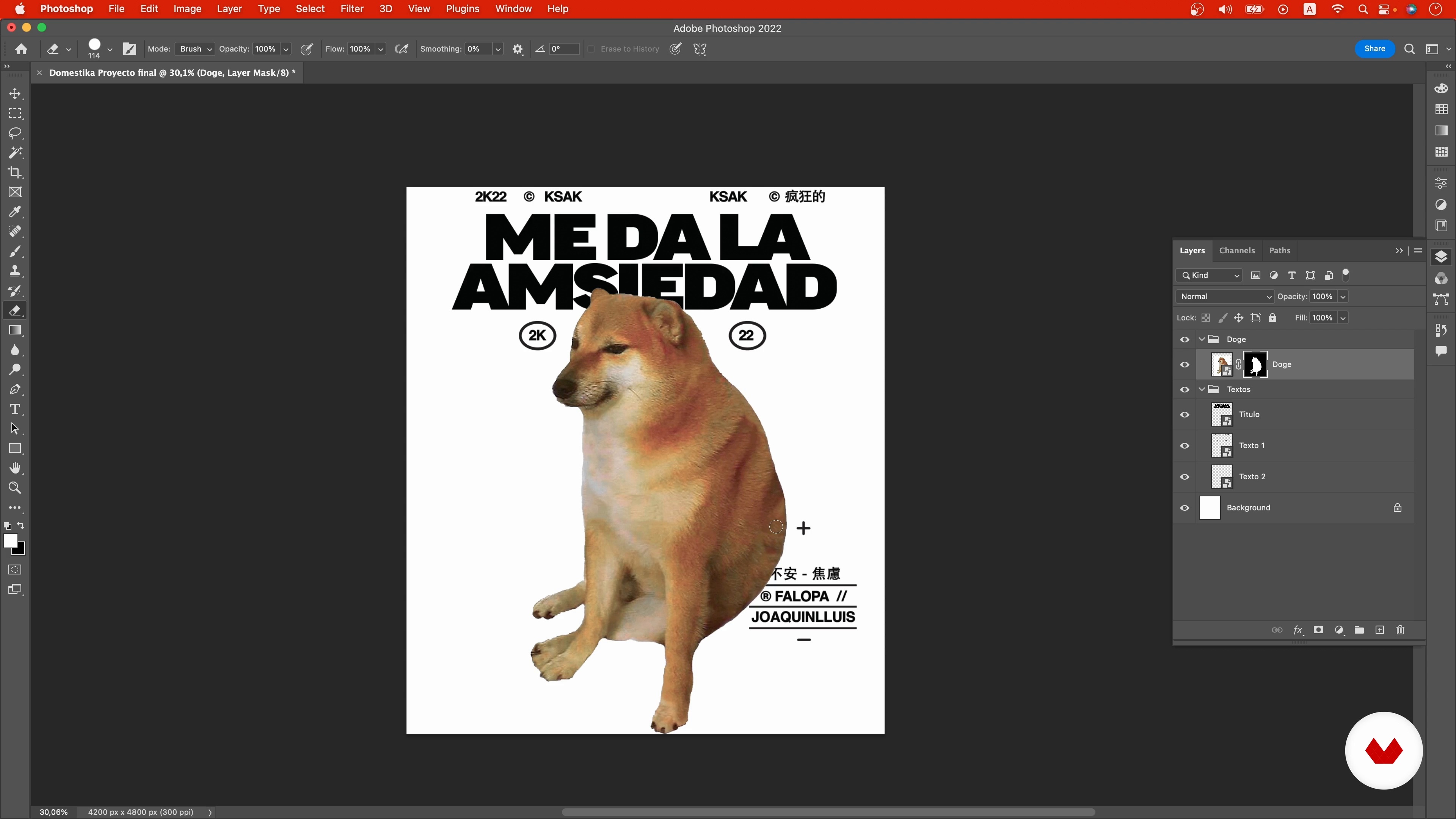
Création d'une typographie pour t-shirt
Traitement d'images 2
Un cours proposé par Joaquín Lluis , Graphiste
À propos de la leçon : Traitement d'images 2
“Je vais maintenant sélectionner une image et commencer à l'intégrer dans ma pièce en définissant sa taille et son ajustement.”
Dans cette leçon, Joaquín Lluis aborde le sujet : Traitement d'images 2, qui fait partie du cours Domestika en ligne : Création d'une typographie pour t-shirt. Découvrez les secrets de la création de t-shirts et exprimez vos idées créatives..
“Maintenant que nous avons bien défini la typographie. dans la partie précédente. nous avons travaillé sur la combinaison typographique. Nous avions d'abord sélectionné la typographie principale pour notre titre. bon. entre-temps. j'ai effectué quelques ajustements supplémentaires. Nous avions donc déjà choisi cette et nous avions décidé de la combiner avec Helvetica Mais je fais encore quelques ajustements. tant au niveau de la taille ainsi que des poids pour chaque élément et leurs relations respectives. et surtout en ajoutant quelques textes plus spécifiques. Par exemple. j'utilise des te...”